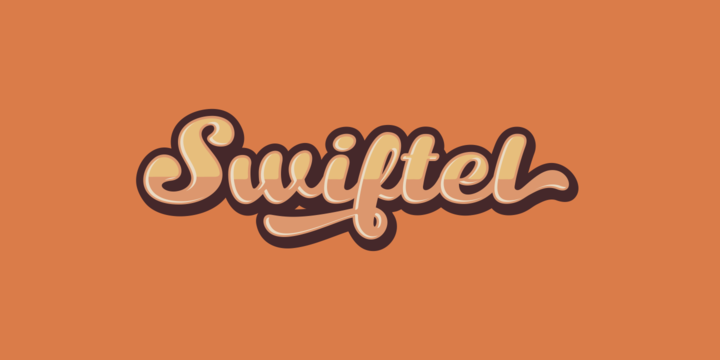
A Swiftel Base é uma fonte tipográfica semicircular que transmite uma sensação única de modernidade. Sujeitável a ser usada no papelaria e design editorial, esta fonte traz vida ao texto com seus três níveis distintos: o layer Base serve como um tipo regular, enquanto os layers Shine, Fill e Outline adicionam profundidade ao texto, criando uma iluminação especial e molduras elegantes. O Shadow solo proporciona sombras acentuadas para dar ao texto um toque de modernidade sofisticada. Swiftel é equipado com as características do tipo opentype para permitir flexibilidade e personalização adicional. Esta fonte oferece uma grande variedade de possibilidades de design, incluindo a criação de logotipos, editoriais, letras grandes e muito mais. Você pode encontrar esta fonte no site http://myfonts.us/rBmg6I.